選擇正確的字體可以使您的設計的可讀性和視覺吸引力大不相同。 根據 Nielsen Norman Group 的一項研究,易於閱讀的字體可以將用戶參與度提高多達 20%。 考慮到這一點,選擇一種不僅看起來很棒而且能增強用戶體驗的字體至關重要。
在本文中,我們將介紹 15 種最適合報紙風格設計的字體。 從經典的襯線字體到現代的無襯線字體,我們都能滿足您的需求。
每種字體都有其獨特的特點和優勢,使其適用於不同類型的項目。
那麼,讓我們深入探索這些奇妙的選擇吧!
最佳高級報紙字體
公告
Noticia 是一種非凡的字體,可以幫助您以經典印刷報紙的風格創建引人入勝的標題。 Noticia 憑藉其簡潔乾淨的外觀,為您的設計項目增添了一絲舊世界的魅力。
該字體具有大寫和小寫字符,以及支持多語言使用的標準標點符號和國際字符。 它不僅允許設計的多功能性,而且還有助於捕捉過去時代傳統報紙的外觀和感覺。
如果您正在尋找一種方法來為您的設計添加經典風格,那麼將 Noticia 結合到您的工作中可能是完美的,特別是如果您正在尋找一種字體以在您的下一個報紙風格設計標題中脫穎而出。
Keytic 中的混亂
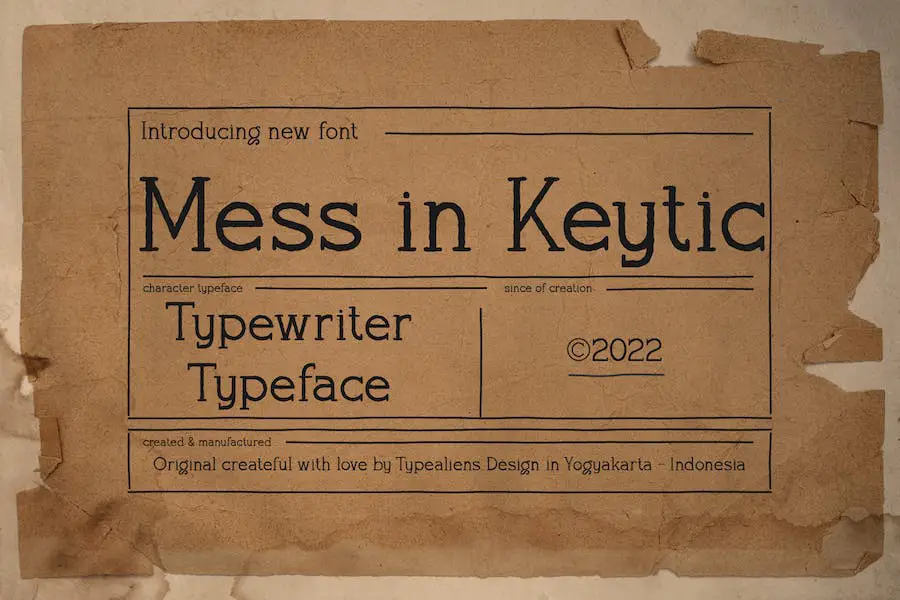
Mess in Keytic 是一種經典字體,其靈感來自打字機字母。 這種字體非常適合創建文本或段落,但它在報紙和雜誌封面上的標題效果非常好。
如果您正在尋找現代報紙字體來增強您的下一個標題,Keytic 中的 Mess 是一個很好的選擇。 它的經典風格為您的項目增添了一絲懷舊之情,同時仍保持足夠的現代感以引起人們的注意。
蒙塔斯
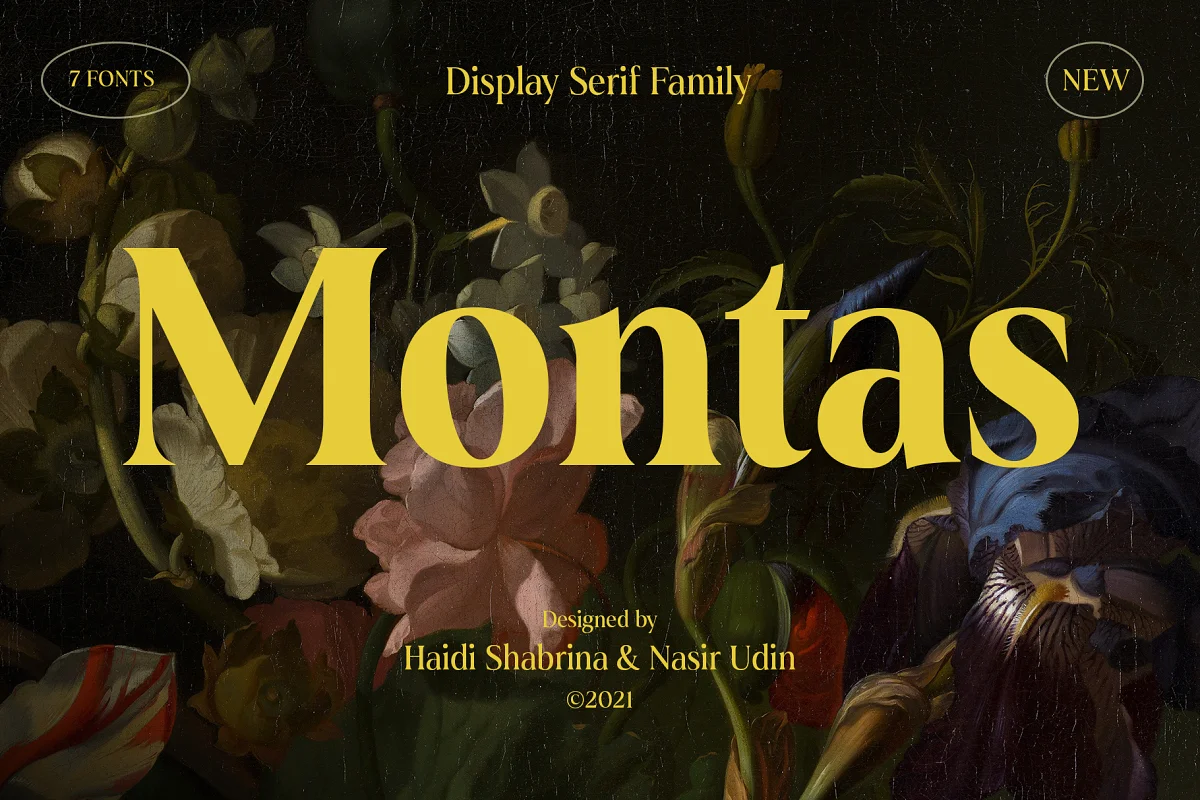
Montas 是一種時尚的襯線字體,非常適合現代報紙設計。 其高對比度和復古主題設計使其從其他字體中脫穎而出,將讀者的注意力吸引到標題和類似的短段落上。
當用於標題時,Montas 的較粗體量特別引人注目,使它們很容易被讀者註意到。 另一方面,這種字體較輕的字體很適合短段落,確保您的內容易於閱讀和吸引人。
如果您想創建現代報紙設計,Montas 絕對值得考慮。 其優雅的顯示襯線風格為任何項目增添了一絲精緻,而其多功能性確保它能夠很好地與各種不同的設計元素配合使用。
照相暗盒
Camera Obscura 是一種複古風格的襯線字體,旨在恢復紐約市過去報紙使用的舊式排版外觀。
這種字體非常適合那些希望創造讓人想起過去時代的設計的人。 每個字母的大膽和銳利確保您創建的每個標題都脫穎而出,使其成為那些希望通過標題產生影響的人的完美選擇。
電訊報
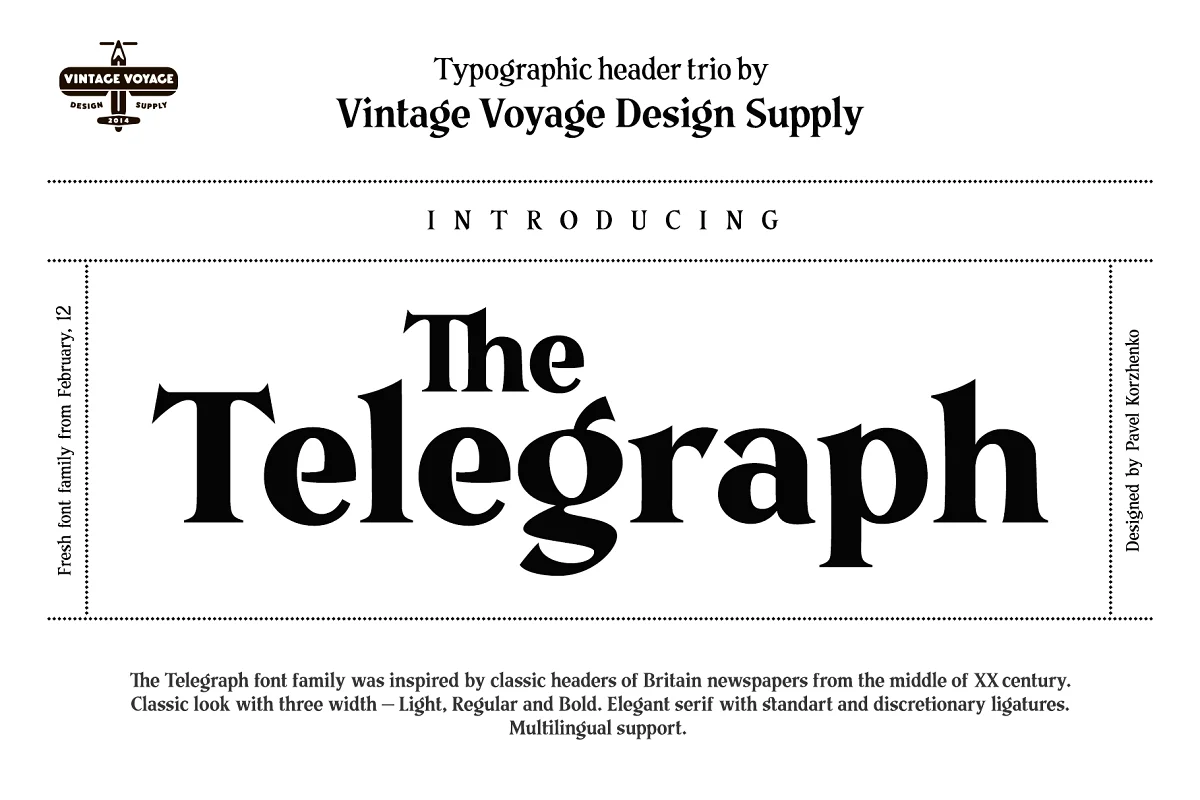
The Telegraph 是一個字體系列,靈感來自 20 世紀中葉英國報紙的經典標題。 它提供三種寬度,Light、Regular 和 Bold,使其在各種項目中用途廣泛。
Telegraph Light 非常適合文本塊,其輕柔的排版可以通過增加大寫字跡來增強效果。 同時,The Telegraph Regular 非常適合簡單的消息、引述、副標題(如果標題是粗體)或廣告標語。
最後,The Telegraph Bold 是主詞、標題、標誌或徽標的絕佳選擇,其外觀大而柔和。
花藝師
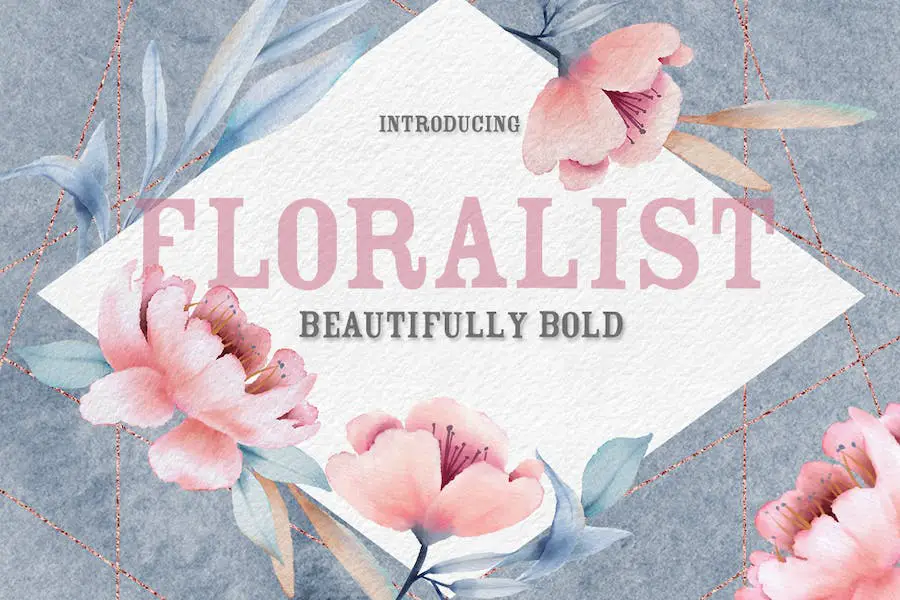
Floralist 是一種大膽而漂亮的字體,為了您的方便,它有 OTF 和 TTF 兩種格式。 其獨特的風格為您的設計增添了高度,使其非常適合製作徽標和其他帶有一絲時髦的創意元素。
雖然此字體僅包含大寫字母且不含標點符號,但它與您最喜愛的腳本字體完美搭配,打造出真正獨特的外觀。
onAir1933
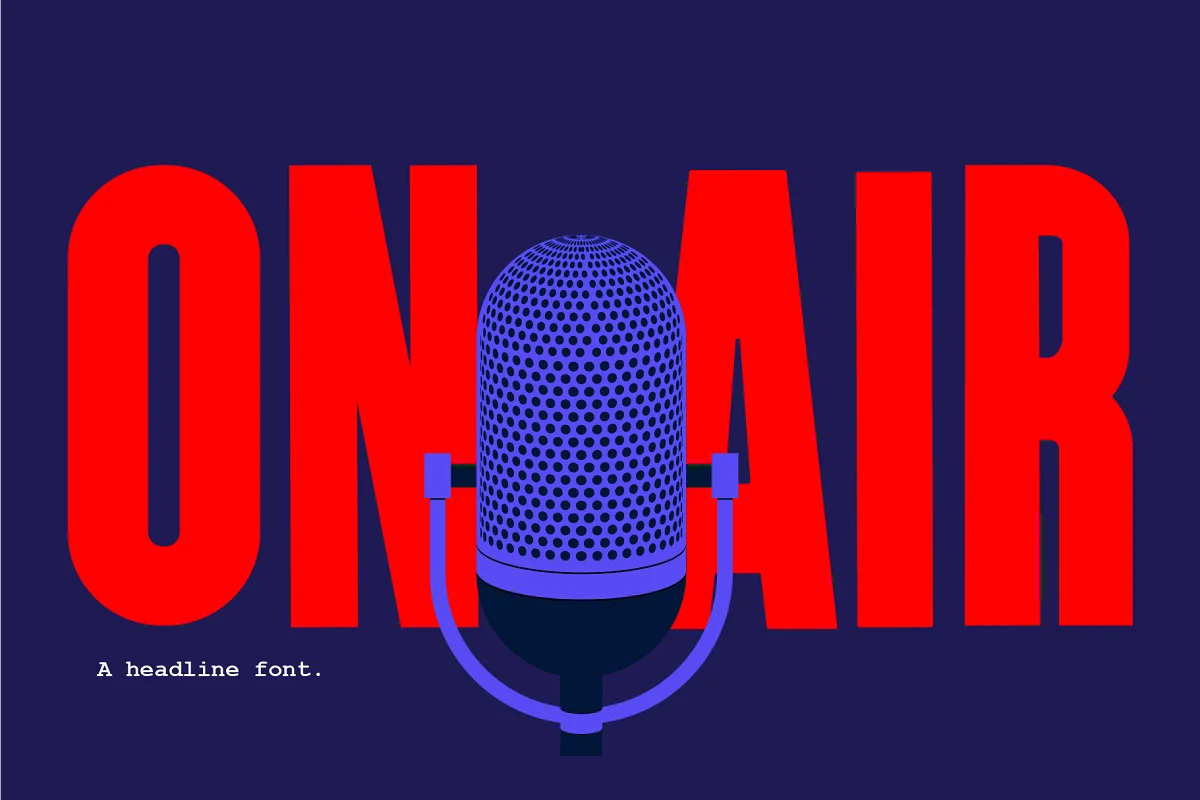
onAir1933 是一種具有獨特歷史和背景故事的字體。 這種字體的靈感來自戰時紙上的頭條新聞和無線電廣播的黃金時代。 這是一個簡化的字體集,傳達了第一次世界大戰期間和之後消息傳遞的實用但令人欣慰的力量。
當您使用這種字體時,它會使您的項目看起來像一個手工設置的凸版印刷機。 它有一種懷舊的感覺,聞起來像舊書和報紙的熱壓,非常適合傳達重要信息。
戈爾多尼
Goldoni 是一種新字體,可為您的設計帶來意大利奢華。 其帶有垂直強調的優雅而簡單的標題襯線使其非常適合標題、徽標、電影海報和報紙展示。
如果您正在為您的下一個標題尋找最好的報紙字體,Goldoni 是一個很好的選擇。 其超乾淨的外觀和寬大的字符間距突出了負空間和細字體之間的對比。 這種字體將幫助您的標題脫穎而出並吸引讀者的注意力。
瓦格納
NT Wagner 以其獨特的現代和復古設計元素的融合,從其他字體中脫穎而出。 其柔和的曲線和簡潔的線條為任何設計賦予精緻的外觀。 襯線字體給人一種經典的感覺,而現代元素則使它清新現代。
馬林魚
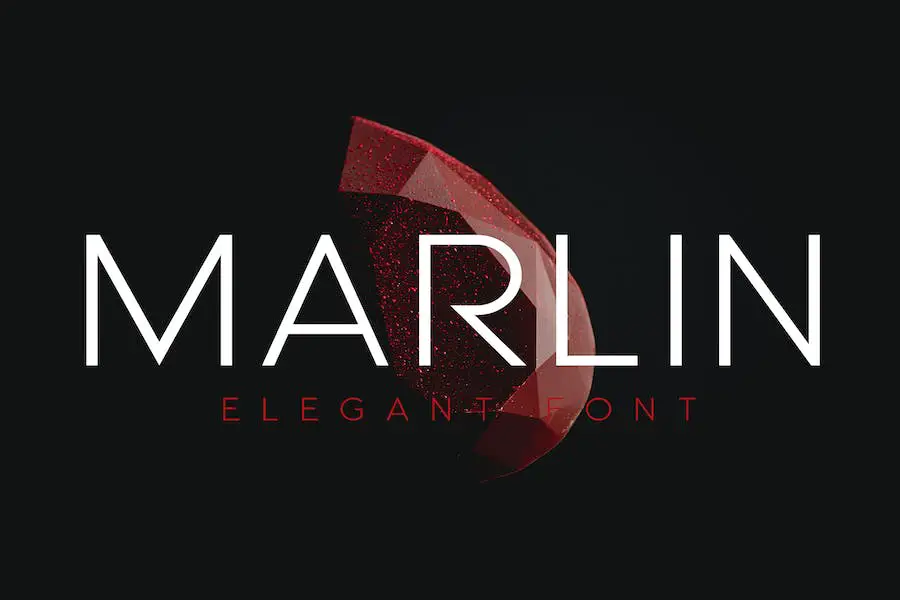
Marlin 是一種奢華字體,可將您的設計項目提升到新的高度。 這種字體非常適合現代報紙和雜誌的佈局、網頁設計、徽標、美容海報以及任何其他需要精緻的項目。
Marlin 具有圓滑時尚的外觀,使其從其他字體中脫穎而出。 其簡潔的線條和優雅的曲線一定會吸引眼球並吸引讀者。無論您是設計網站還是創建印刷出版物,Marlin 的多功能性使其成為任何項目的絕佳選擇。
最好的免費報紙字體
牛津
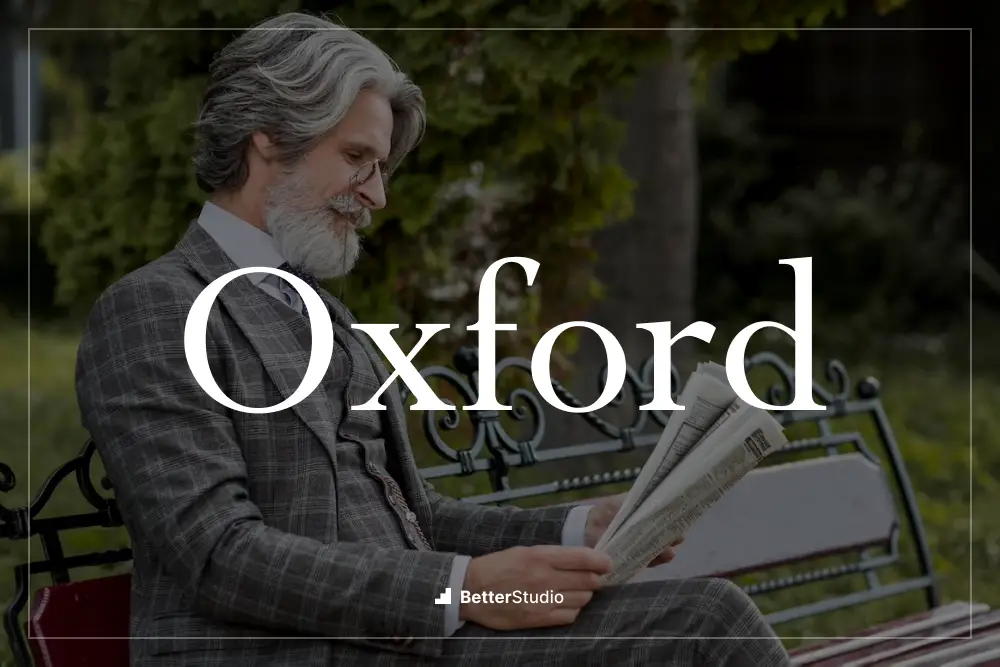
Oxford 是一種現代報紙字體,它提供完整的提示以在小磅值和 471 對字距調整時準確渲染。 這種字體是標題和正文的理想選擇,應能很好地呈現低至 6 點,使其成為網絡和印刷媒體的完美選擇。
牛津提供大小寫字母、0 到 9 的數字以及各種標點符號。 但是,此字體中不包含變音符號。
加的夫
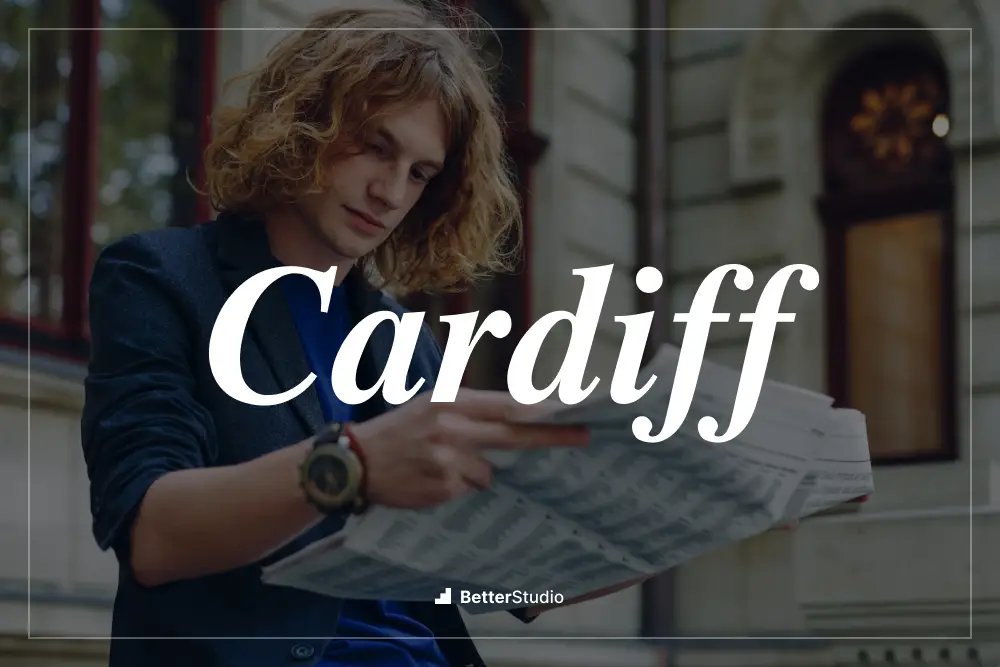
Cardiff 是一種現代報紙字體,有四種不同的風格,由 Roger White 設計。 該字體系列提供簡單經典的外觀和現代風格,非常適合標題或任何需要乾淨、專業外觀的設計項目。
Cardiff 字體系列中提供的四種不同樣式包括常規、斜體、粗體和粗體斜體。 每種樣式都提供獨特的外觀,同時仍保持字體系列的整體感覺。 常規樣式非常適合正文,而粗體和斜體樣式則是標題和副標題的絕佳選擇。
報紙
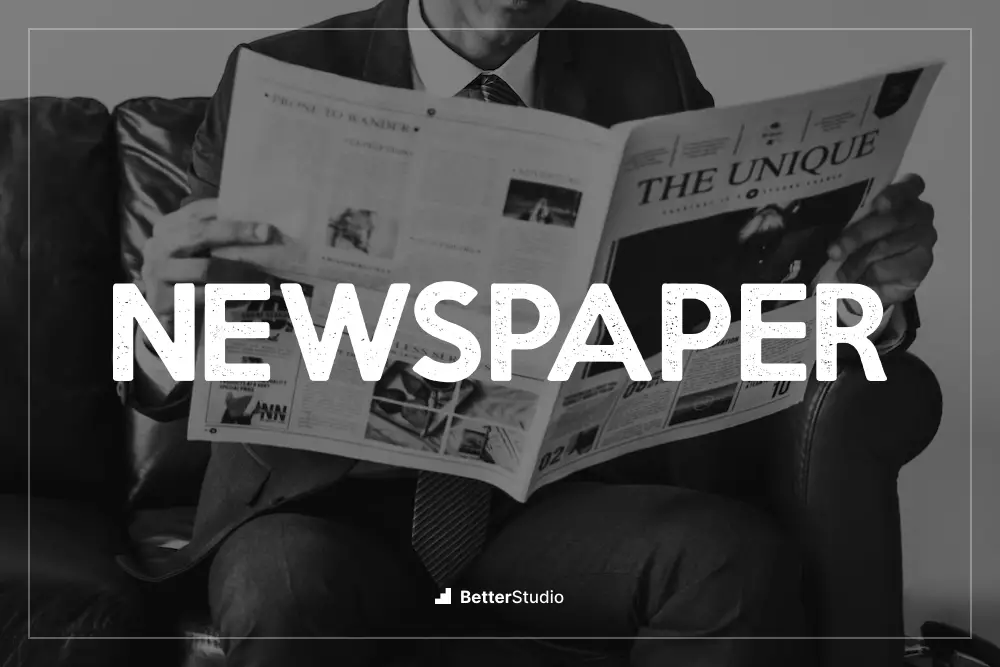
Billy Argel Fonts 的 NEWSPAPER Font 是一種美觀且用途廣泛的字體,可以為您的設計增添一絲優雅。 這種字體非常適合那些正在為下一個標題尋找現代報紙字體或報紙字體的人。
NEWSPAPER 字體有兩個版本:半展開和半展開斜體,使設計師可以輕鬆地為他們的項目選擇合適的樣式。 半展開版本具有乾淨現代的外觀,而半展開斜體版本為任何設計增添了一絲精緻。
卡爾勞特
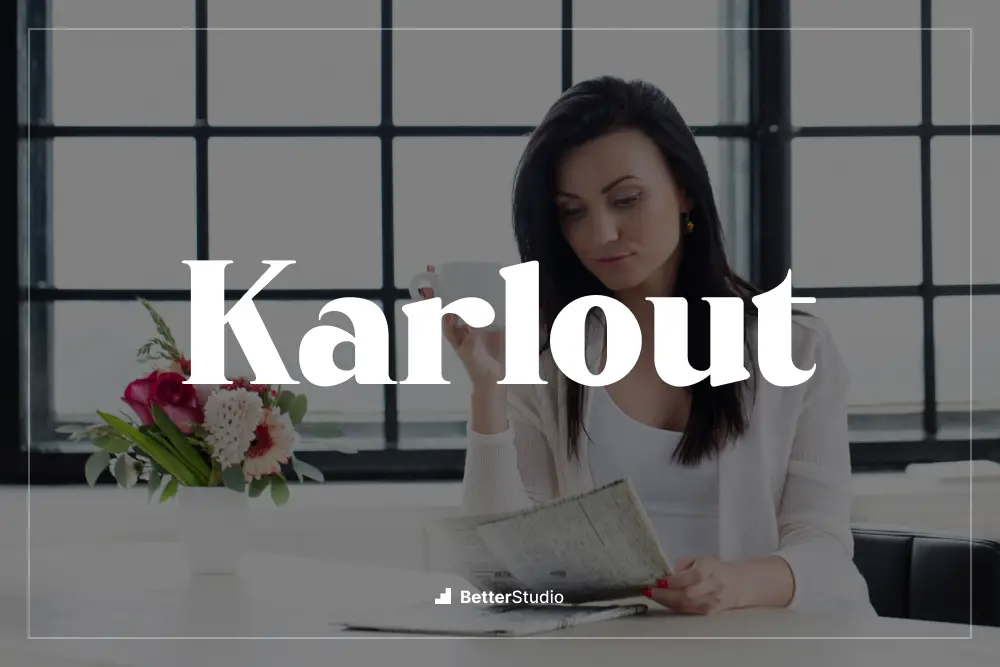
Raditya Type Studio 的 Karlout 字體是一種現代報紙字體,可以提升您的設計項目。 這種字體帶有乾淨利落的線條,非常適合新聞標題設計。 此外,它還具有各種功能,例如大寫和小寫字母、標點符號和數字。
Karlout Font 獨特的設計使其從其他報紙字體中脫穎而出。 它的粗體筆劃即使在小尺寸上也很容易閱讀。 您也可以將此字體用於標題、副標題和正文。
每日鏡報
Billy Argel Fonts 的 Dailymirror Font 是一種現代字體,可以改變您的報紙設計並賦予它們獨特的現代外觀。 該字體免費供個人使用,有兩個文件,常規字體和斜體字體。
Dailymirror 簡潔的線條和大膽的筆觸使其即使在小尺寸時也易於閱讀,斜體版本為任何標題增添了一絲優雅。 無論您是設計雜誌封面還是報紙頁面佈局,Dailymirror 的多功能性使其成為現代報紙字體的絕佳選擇。
如果您正在尋找對傳統報紙排版的全新詮釋,請試試 Dailymirror。 其簡單而時尚的設計將幫助您的標題脫穎而出並吸引讀者的注意力。